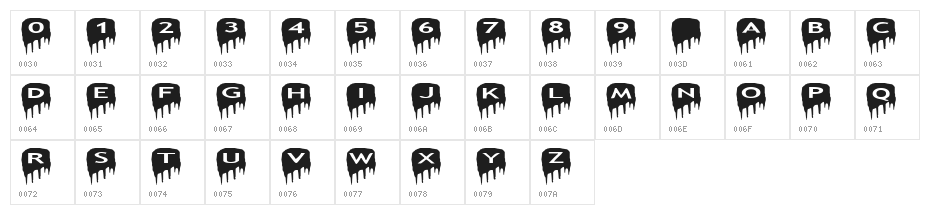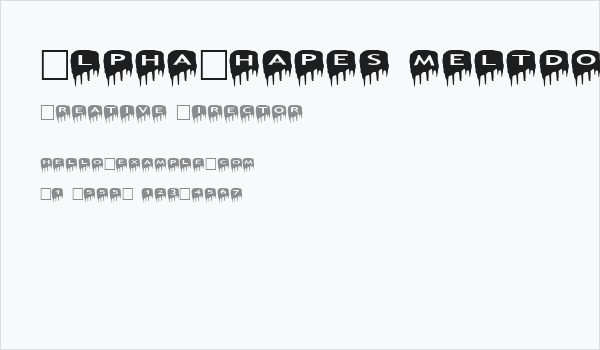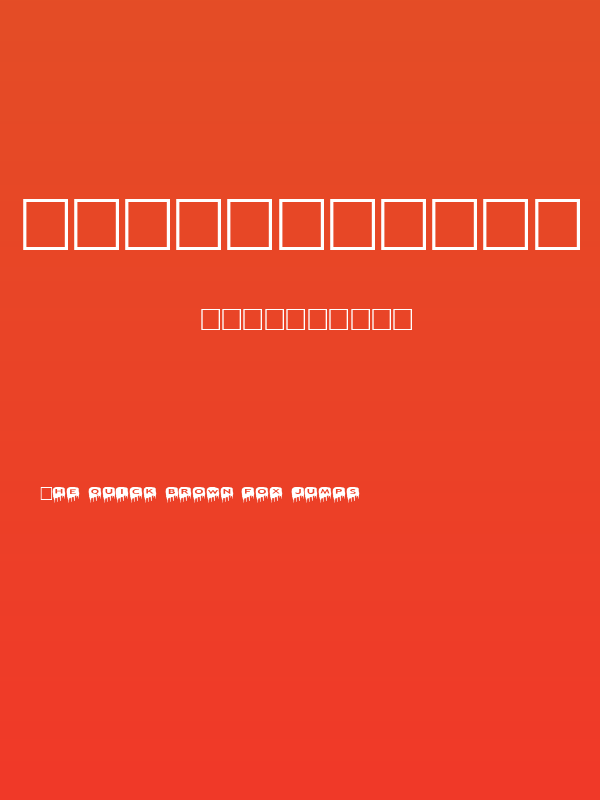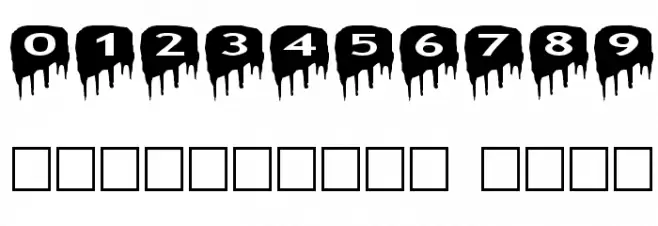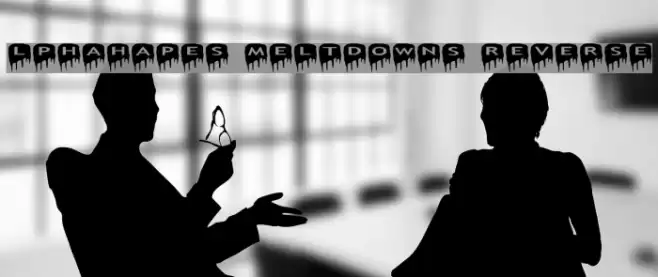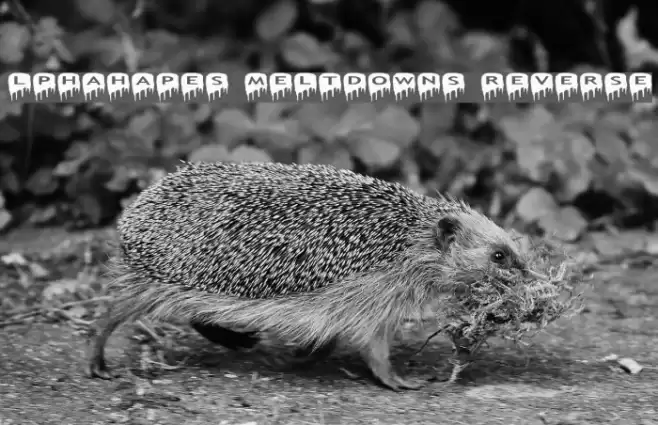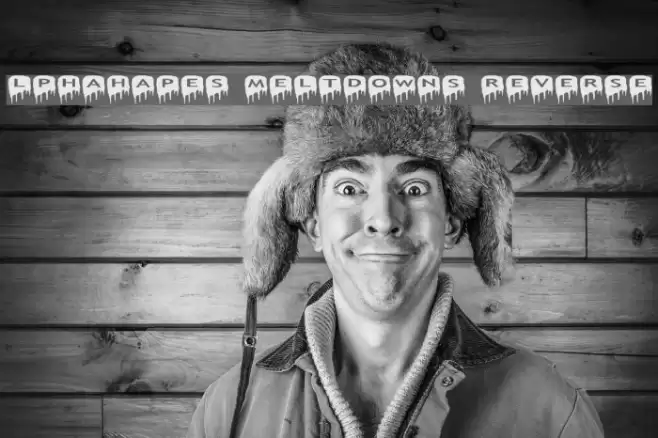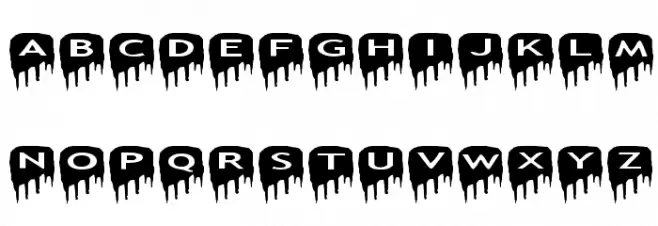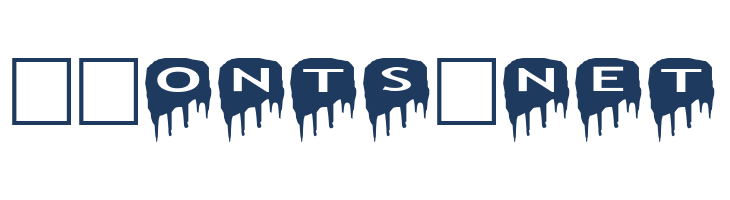
AlphaShapes meltdowns reverse Font
| Vorgeschlagene Projekte | Ideal for Halloween-themed projects, horror movie posters, edgy branding, or any design requiring a bold, unconventional look. |